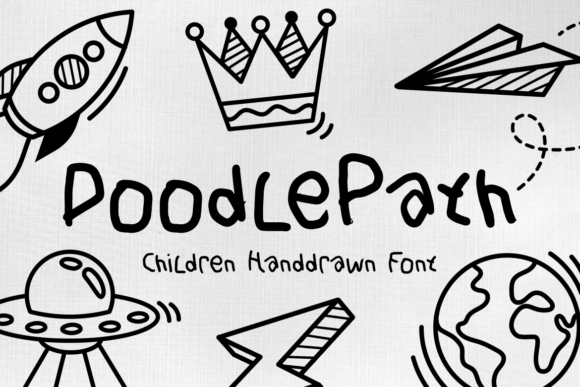
Doodle Path
Doodle Path – La police dessinée à la main qui fait revivre l’enfance
Si vous cherchez une typographie qui respire la joie, la créativité et le charme « fait‑maison », Doodle Path est la réponse. Conçue spécialement pour les projets liés à l’univers des enfants, cette police manuscrite capture l’esprit des gribouilles spontanées et des dessins colorés que chaque petit artiste laisse sur le papier.
Pourquoi Doodle Path se démarque ?
- Style unique : chaque caractère est dessiné à la main, avec des lignes audacieuses et des doodles ludiques qui rappellent les premiers crayons de couleur.
- Lisibilité optimale : malgré son côté espiègle, la police reste très claire, idéale pour les titres, les invitations et le texte de corps.
- Polyvalence exceptionnelle : parfaite pour les cartes d’invitation d’anniversaire, les couvertures de livres pour enfants, les logos, les emballages, les affiches et même les titres de films.
- Émotion et nostalgie : Doodle Path n’est pas seulement une police, c’est une invitation à revivre les moments colorés de l’enfance.
Idées d’utilisation créative
Voici quelques inspirations pour exploiter le plein potentiel de Doodle Path :
- Création d’invitations personnalisées pour les fêtes d’anniversaire ou les ateliers créatifs.
- Conception de couvertures de livres illustrés, de cahiers d’activités ou de cartes de vœux.
- Développement de logos et d’identités visuelles pour des marques « kids‑friendly » ou des écoles.
- Design d’emballages ludiques pour jouets, bonbons ou produits de papeterie.
- Réalisation d’affiches, de flyers et de bannières Instagram qui captent immédiatement l’attention.
Verdict final
En résumé, Doodle Path est une police qui allie fun, chaleur et professionnalisme. Que vous soyez designer freelance, responsable de la communication d’une marque ou parent créatif, elle vous aidera à injecter une dose de gaieté et de couleur dans tous vos supports. Ne manquez pas l’opportunité de transformer vos créations en véritables souvenirs d’enfance !